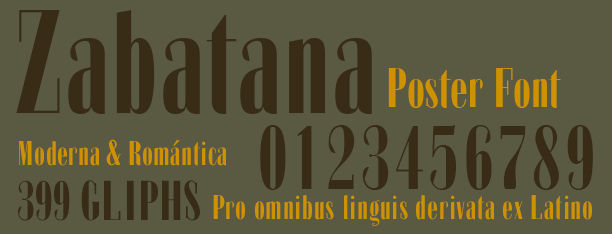
Tipografía para uso personal. Descarga gratis la versión Itálica desde mi web. See free download of Italic Version in my Web Lincencia comercial disponible / Available commercial license: http://defharo.com/fonts/zabatana-poster-font/ fuente comprimida de estilo modernista y romántico y sin serif, inspirada en tipografías decorativas de los principios del S.XX. El diseño de la fuente está realizado para usarla en tamaños por encima de los 24pt, es una tipografía de proporciones heavy y comprimida, y su utilización óptima en diseño gráfico viene dada para el uso en carteles, poster, afiches y grandes rótulos, es una poster font, también sirve perfectamente para títulares en diseño editorial, maquetación de publicaciones, etc. |